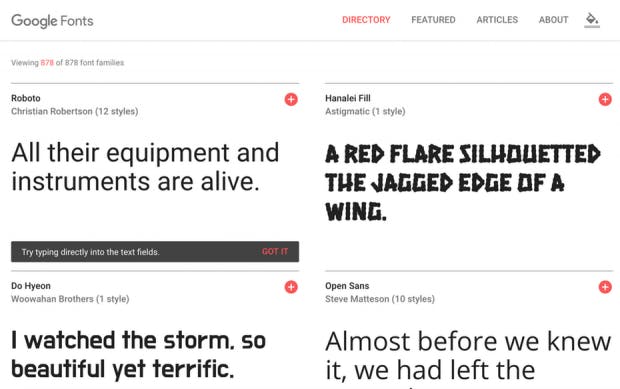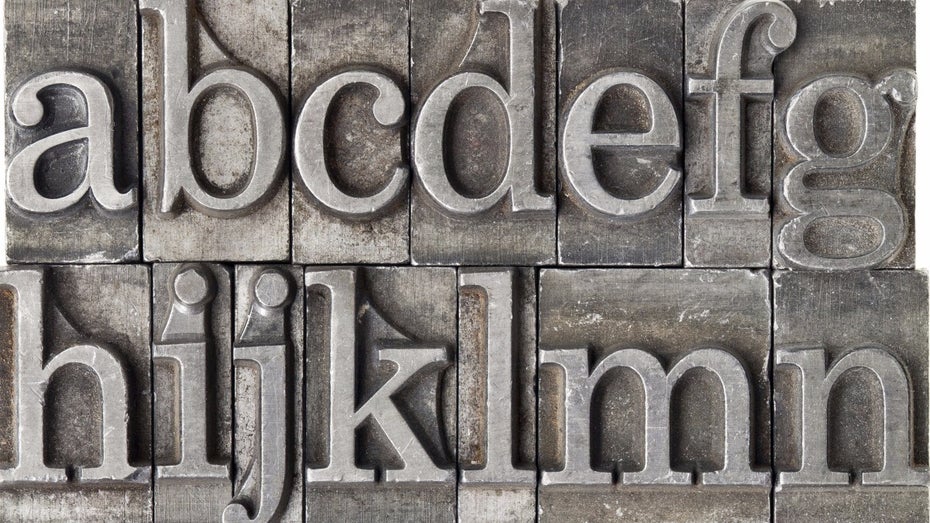
Wie du Schriftarten für dein Webdesign auswählst
Die richtige Schriftart kann großen Einfluss auf das endgültige Look-and-Feel deines Webdesigns haben. Es scheint nur eine kleine Sache zu sein, aber die richtige Schriftart hat das Potenzial, dein Webdesign auf die nächste Stufe zu heben. In diesem Artikel erfährst du alles, was du wissen musst, wenn du die Schriftarten für dein Webdesign auswählst.
Hast du Marken-Guidelines? Halte dich an sie
Marken-Guidelines legen fest, wie die Elemente deiner Marke verwendet werden. Deine Marken-Guidelines sind ein essenzielles Tool, um eine zusammenhängende Markenstrategie zu vermitteln. Es gibt eine Reihe von Regeln, die dabei helfen, eine einheitliche Identität zu kreieren, wenn du mehrere Elemente deiner Marke miteinander verbindest, indem sie deine Farben, dein Logo und natürlich deine Typografie definieren.
Wenn es also bereits einen Markenguide gibt, mit dem du arbeiten kannst, halte dich auch an ihn, wenn du dein Webdesign erstellst. Wenn du noch keinen hast, kannst du hier sehen, wie man einen Marken-Styleguide erstellt.
Die Bedeutung von Einheitlichkeit
Die Versuchung ist groß, mit neuen Schriftarten zu experimentieren, wenn du dein Webdesign erstellst, aber tu es nicht! Jedes Mal, wenn jemand eine Visitenkarte von dir bekommt oder deine Website besucht, erhält er einen kurzen Einblick in die DNS deiner Marke und das Gesamtdesign deines Unternehmens. Diese Wahrnehmungen müssen zusammen ein vollständiges und einheitliches Bild ergeben – ansonsten könnte deine Marke am Ende aussehen wie ein großes Durcheinander ohne Wiedererkennungswert. Daher ist es wichtig, über all deine digitalen Plattformen und gedruckten Materialien hinweg einheitlich zu sein, wenn es um Farbe, Stil und – du ahnst es – Schriftarten geht.
Angleichen deiner bestehenden Markenschriftarten
Marken-Guidelines enthalten Schriften und Familien, Schriftgrößen und die Hierarchie der verwendeten Schriftarten, damit du sie sofort in dein Webdesign einbauen kannst. Wenn deine Marke eine unbekannte Schriftart verwendet, können Tools wie „What The Font“ auf Myfonts.com dir dabei helfen, den Namen der Schriftart herauszufinden.
Wenn deine Marke eine individuelle Typografie verwendet, wird der Designer versuchen, eine ähnlich aussehende Webfont zu finden, die er in deinem Webdesign verwenden kann. Aufgrund unterschiedlicher Browser kann es passieren, dass deine selbsterstellte Typografie weniger klar und sauber aussieht, als du das gerne hättest. Daher nutzen viele Webdesigner Google Fonts, um so nah wie möglich an deine Markentypografie heranzukommen.
Du hast noch keine Schriftarten und Guidelines?
Du hast noch keine Schriftarten für deine Marke gewählt? Hier sind ein paar wichtige Dinge, über die du dir Gedanken machen solltest, wenn du eine Schriftart für dein Webdesign wählst:
Finde die Persönlichkeit deiner Marke
Deine Schriftart muss die Persönlichkeit deiner Marke repräsentieren, damit dein Design perfekt ist. Handelt es sich um ein traditionelles Unternehmen oder ist es minimalistisch und modern oder lustig und abgedreht? Würdest du dein Unternehmen als retro, klassisch, ausgefallen oder flippig beschreiben? Es gibt noch mehr Fragen, die du dir stellen solltest, um die einzigartige Persönlichkeit deiner Marke zu ermitteln.
Sobald du diese Fragen beantwortet hast, wirst du ein Verständnis für die Persönlichkeit deiner Marke und das Look-and-Feel deines Webdesign haben. Basierend auf dieser Identität kannst du nun die richtigen Schriftarten für deine Marke wählen.
Wähle Schriftarten, die zu deiner Marke passen
Sagen wir mal, du hast einen Laden für Vintage-Klamotten mit einem coolen, modernen Vibe. Du könntest eine oldschool aussehende, flippige Schriftart für die Überschriften mit einer klassischen serifenlosen Schrift für den Fließtext kombinieren. Wenn du zum Beispiel eine schöne altmodische Schriftart wie Arvo für deine Überschriften verwendest, empfiehlt es sich, eine Sans-Serif-Schrift wie Open Sans, die bekannt für ihre Lesbarkeit ist, für deinen Fließtext zu nehmen. Das gibt einen ausgeglichenen Look, der sowohl zeitlos als auch modern ist und perfekt zu deiner coolen Retro-Marke passt.
Oder sagen wir, du hast eine Anwaltskanzlei oder eine hochwertige Kosmetikmarke und deine Typografie soll Vertrauen und Professionalität mit einem Hauch Klasse kommunizieren. Du kannst stylish und doch klassisch und elegant sein mit Serifenschriften wie Frank Ruhl Libre oder Playfair Display, um deinen potenziellen Kunden wirklich zu zeigen, dass du absolut zuverlässig bist und erstklassigen Service bietest. Wenn du mehr darüber erfahren willst, hat Venngage einen guten Artikel über Schrift-Psychologie geschrieben, um dir bei der richtigen Wahl zu helfen.
Egal, für welche Schriftart du dich für deine Markenidentität entscheidest, achte darauf, dass du eine websichere Schriftart wählst, die leicht zu nutzen und passend für die Mehrzahl der Browser ist.
Was sind websichere Schriftarten?
Eine websichere Schriftart zu verwenden, bedeutet, dass deine Besucher nicht eine bestimmte Schriftart auf ihrem Computer installiert haben müssen. Früher, vor zehn oder mehr Jahren, gab es ungefähr 13 Schriftfamilien und Webdesigner mussten darauf achten, nur die paar Schriftarten zu verwenden, die auf den meisten Computern angezeigt wurden. Heutzutage ist Google Fonts der Goldstandard, der einwandfrei in jedem Browser angezeigt wird.